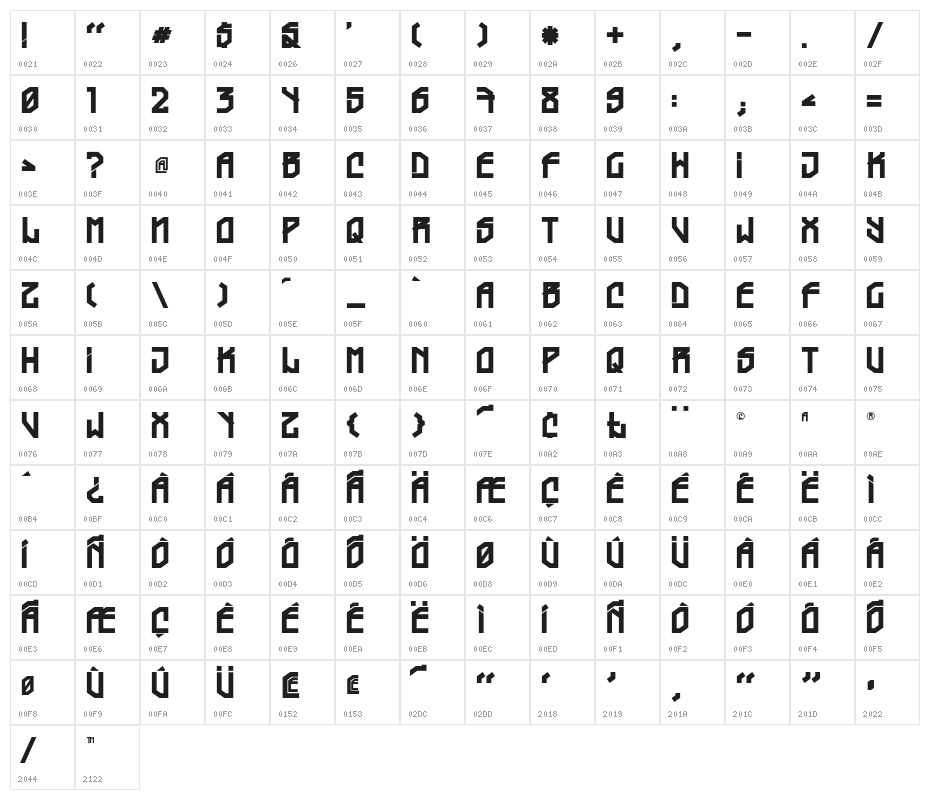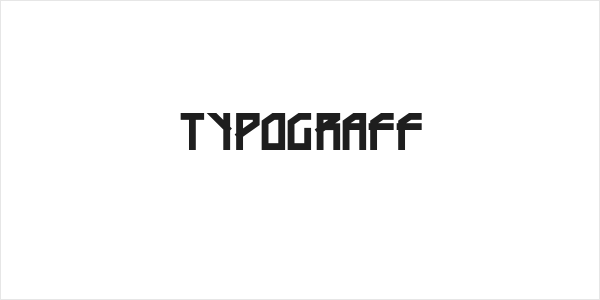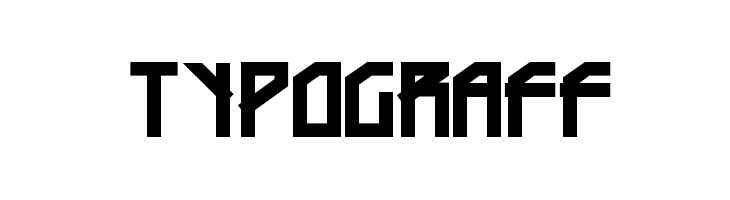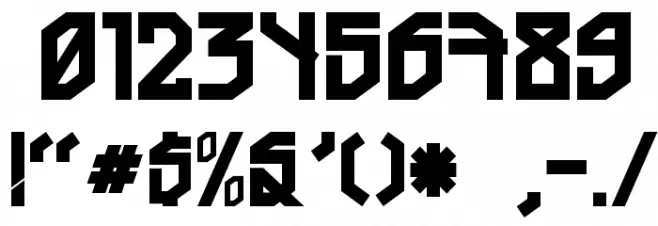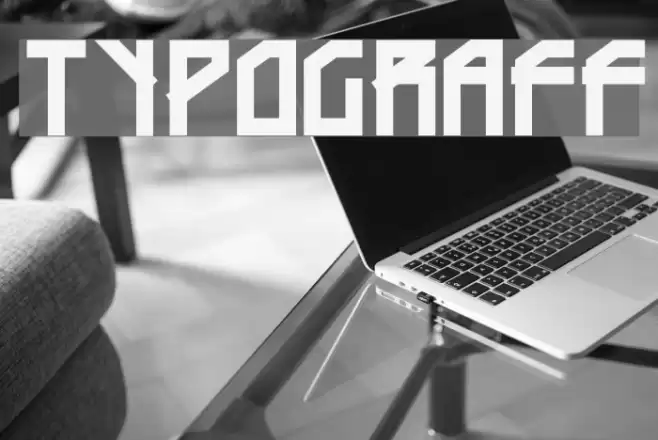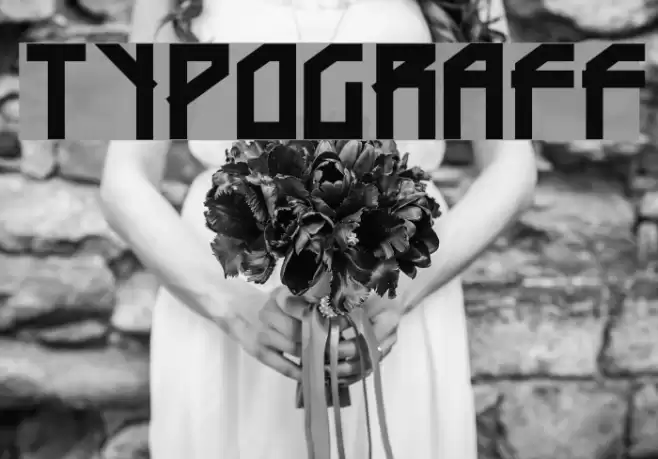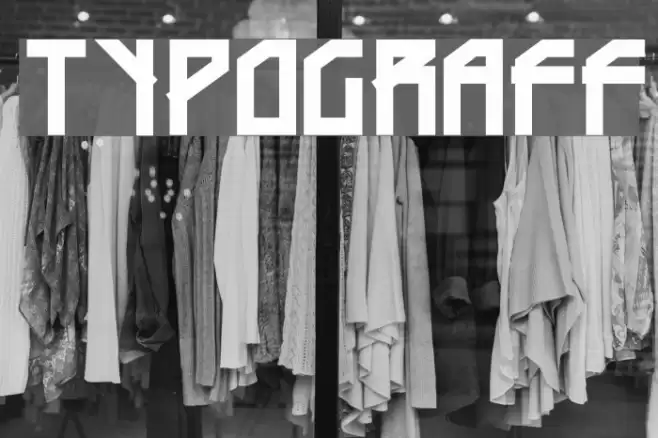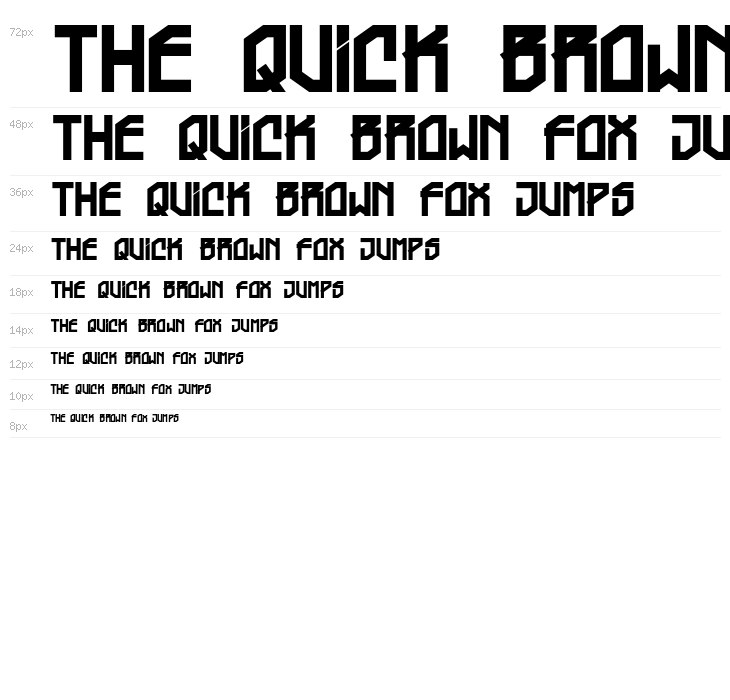
Typograff Font
✎ Thick
| Рекомендуемые проекты | Ideal for branding, posters, video game graphics, and any project requiring a strong, modern aesthetic. |